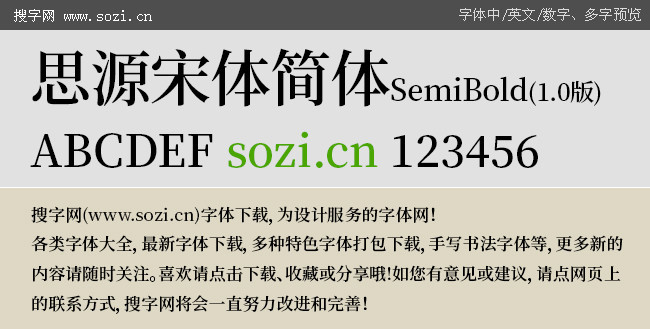
思源宋體簡(jiǎn)體SemiBold
搜字網(wǎng)提供一款思源宋體簡(jiǎn)體SemiBold中文字體下載,思源宋體是一款由谷歌聯(lián)合Adobe發(fā)布全新開源字體,是一款免費(fèi)、開源宋體字體。有 65535 個(gè)字形,可共同呈現(xiàn)一致的視覺美感。本作品適用于書籍排版、報(bào)紙排版、畫冊(cè)設(shè)計(jì),網(wǎng)頁(yè)設(shè)計(jì)等應(yīng)用。